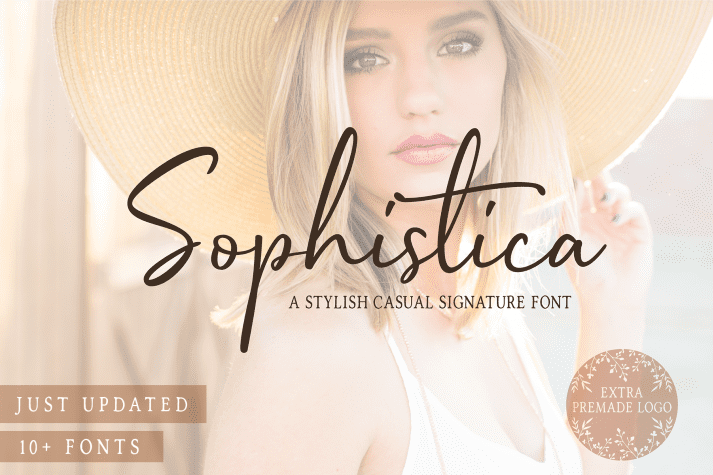
Этот дуэт шрифтов представляет собой комбинацию подписи и смелых стилей. Это отлично подходит для вашего логотипа, ручной росписи надписи, печатных котировок, значков, знаков отличия, упаковки, заголовка, плаката, футболки / одежды, поздравительных открыток и приглашений на свадьбу и т. д